Пользователи жалуются на размытые шрифты в Windows 8.1
Интерфейс Metro, со временем переименованный в Modern UI, который появился в Windows 8 в 2012 году, очень тяжело приживался среди пользователей. В тот период многие начали только задумываться над переходом с Windows XP на более современные ОС. Со временем клиенты Microsoft привыкли к изменениям и стали с удовольствием пользоваться новым плиточным интерфейсом, особенно те, кто работал с сенсорными экранами.
По мере перехода на операционные системы нового поколения все больше пользователей отмечают проблему размытых шрифтов интерфейса, которые трудно читать. На сайте Windows UserVoice, который используется Microsoft для сбора отзывов и пожеланий клиентов, предложение об использовании более четких шрифтов для интерфейса набрало 4 000 голосов и огромное количество комментариев.
Данная проблема острее всего выражается в том, что трудно использовать приложения Windows Store на настольных устройствах независимо от того, какое разрешение экрана используется.
В комментариях к предложению участники сообщества изложили наиболее простой путь к решению проблемы — использование ClearType для работы сенсорных устройств. Это позволит запускать универсальные приложения на ПК без существенных потерь во внешнем виде.
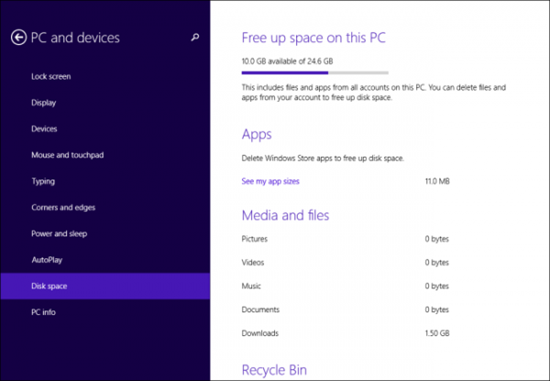
Один из пользователей отметил, что Microsoft может взглянуть на работу платформ конкурентов и, таким образом, придумать способ улучшить качество шрифтов в современных версиях Windows. «Проблему можно решить навсегда, если они применят технологию обработки, используемую на других платформах, таких как Linux и OS X! Были времена, когда я работал с Safari для Windows просто потому, что браузер использовал четкие шрифты, которые были доступны только здесь», — говорится в сообщении.